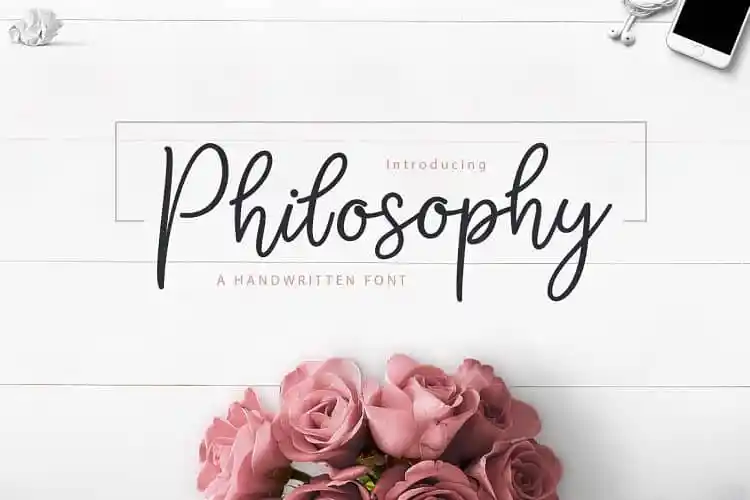
Philosophy Script Font – Download Grátis
Descubra a Philosophy Script Font, uma tipografia script moderna criada para criar impressionantes assinaturas e projetos exclusivos. Esta fonte é ideal para eventos únicos como casamentos, festas, cartões de convite e cards de chegada, bem como menus de mesa, cabeçalhos em blogs personalizados, endereços customizados e selos. A Philosophy Script combina com a elegância da tipografia clássica enquanto também tem o charme moderno das fontes script, oferecendo um equilíbrio entre sofisticação e criatividade perfeita para qualquer projeto. Experimente agora e veja como esta font pode transformar seus projetos em algo único e memorável.